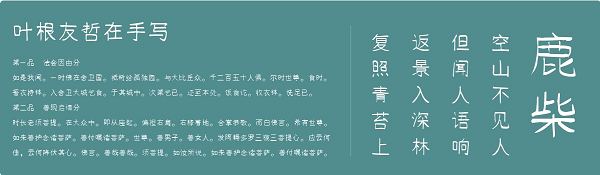
葉根友哲在手寫(xiě)字體是由葉根友全新發(fā)布的一款手寫(xiě)字體,該字體維系一貫的手寫(xiě)字體特色,字里行間帶有一絲絲文雅舒適感,能夠讓用戶(hù)獲得一首完美的字體,喜歡的用戶(hù)快來(lái)綠色資源網(wǎng)下載吧!
葉根友哲在手寫(xiě)是葉根友字庫(kù)全新開(kāi)發(fā)的一款優(yōu)雅的手寫(xiě)體,該字體筆畫(huà)設(shè)計(jì)中融入了書(shū)寫(xiě)的韻味,講究線(xiàn)條之美,使筆劃挺拔有力,剛?cè)嵯酀?jì)筆畫(huà)粗壯有力,能夠應(yīng)用于文本裝潢、信息展示、網(wǎng)頁(yè)設(shè)計(jì)、篆刻制模、數(shù)據(jù)制作、裝潢設(shè)計(jì)、計(jì)算藝術(shù)設(shè)計(jì)、視覺(jué)設(shè)計(jì)、字帖等一切合法應(yīng)用場(chǎng)景,有喜歡的朋友可免費(fèi)下載收藏。